许多人从来没有个性化过,为了追求认同感,模仿着大众的审美和姿态。渐渐地,每个人都会“泯然众人矣!”独一无二的人,应该有独一无二的姿态,别人方方正正的仿宋体,我就来个不走寻常路的法棍体,表明自己的态度,你是你,我是我!
个性字体,突出一个个性,而所有设计方式里,最能体现个性特点的就是手写字了。因为手写字,每个人写出来的,都不一样,即使同样的手法与技巧,所以每个手写字都是独一无二的,而其他的印刷体、所谓的创意体等,设计师都可以用相同的流程设计出一模一样的来。所以手写体算是最好的个性字体了。
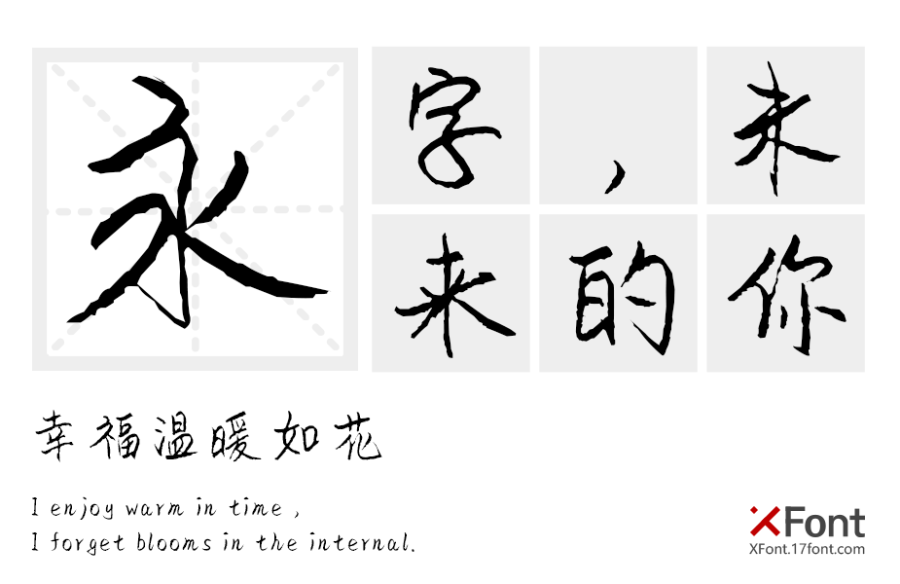
XFont字库品牌前身为“X手迹”,里面含有大量的手写字体,而且这些手写字体的手迹来自于不同年龄段的作者,他们写出来的字,代表着他们的人生阅历和性格,或张扬、或沉稳、或厚重、或纤柔。